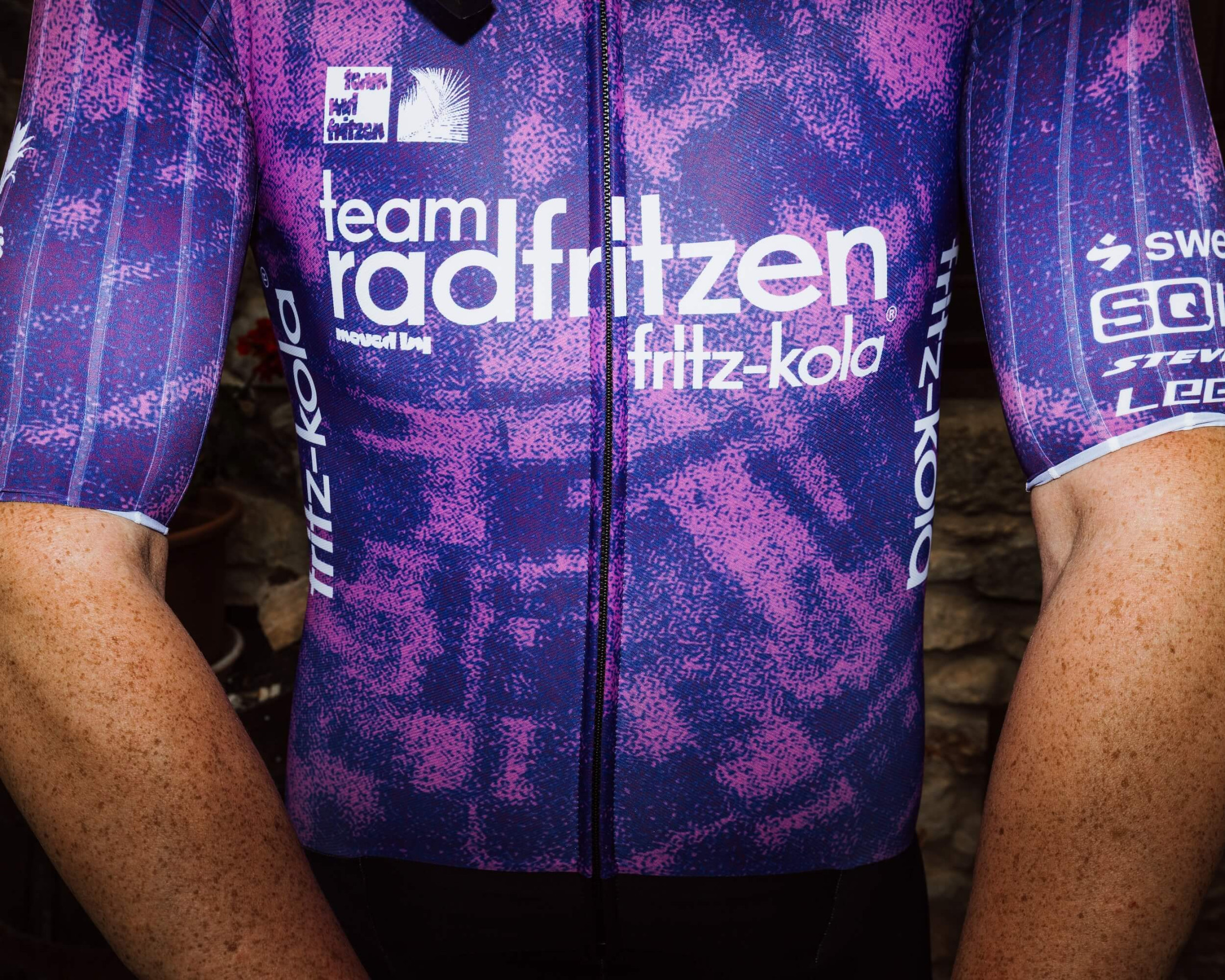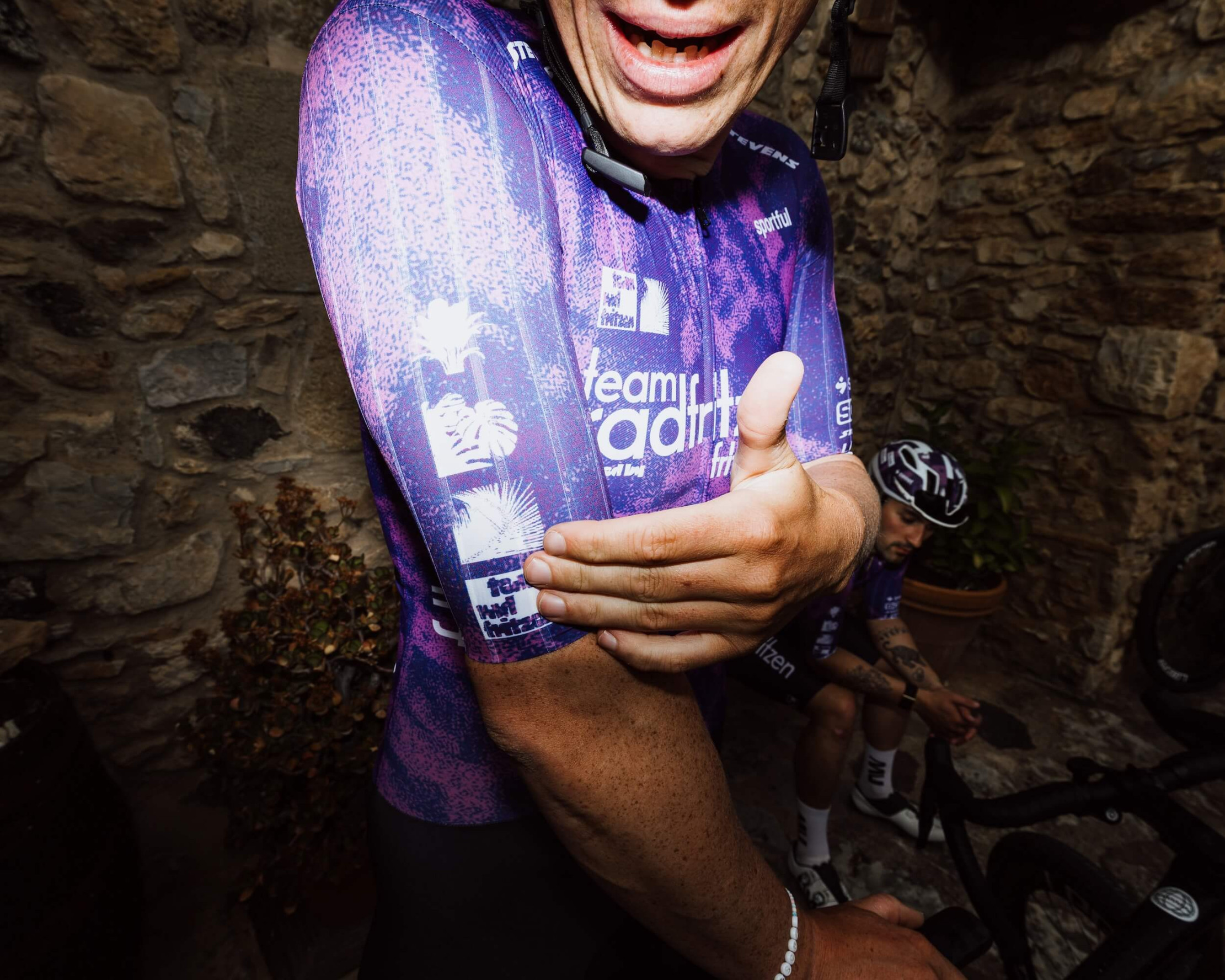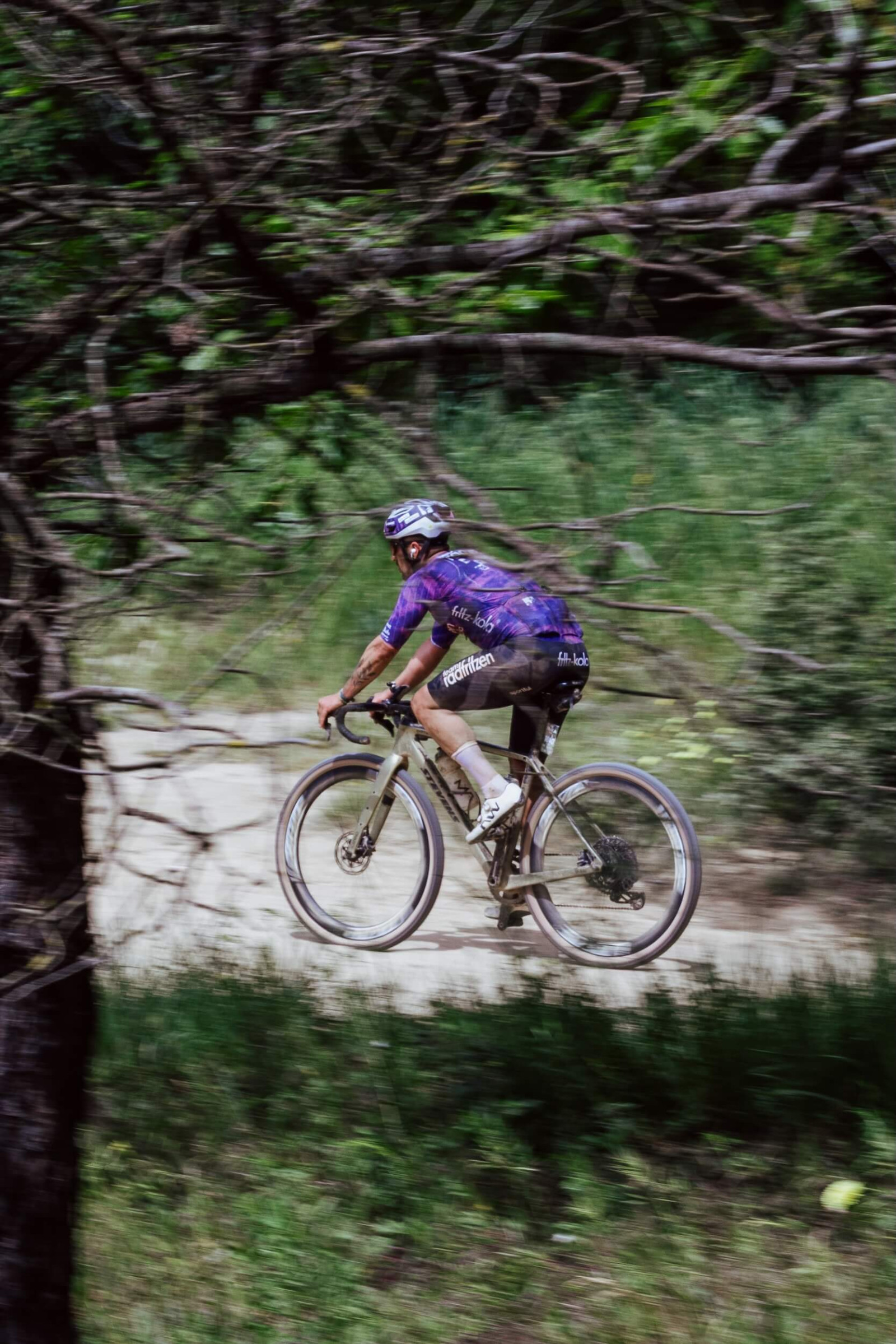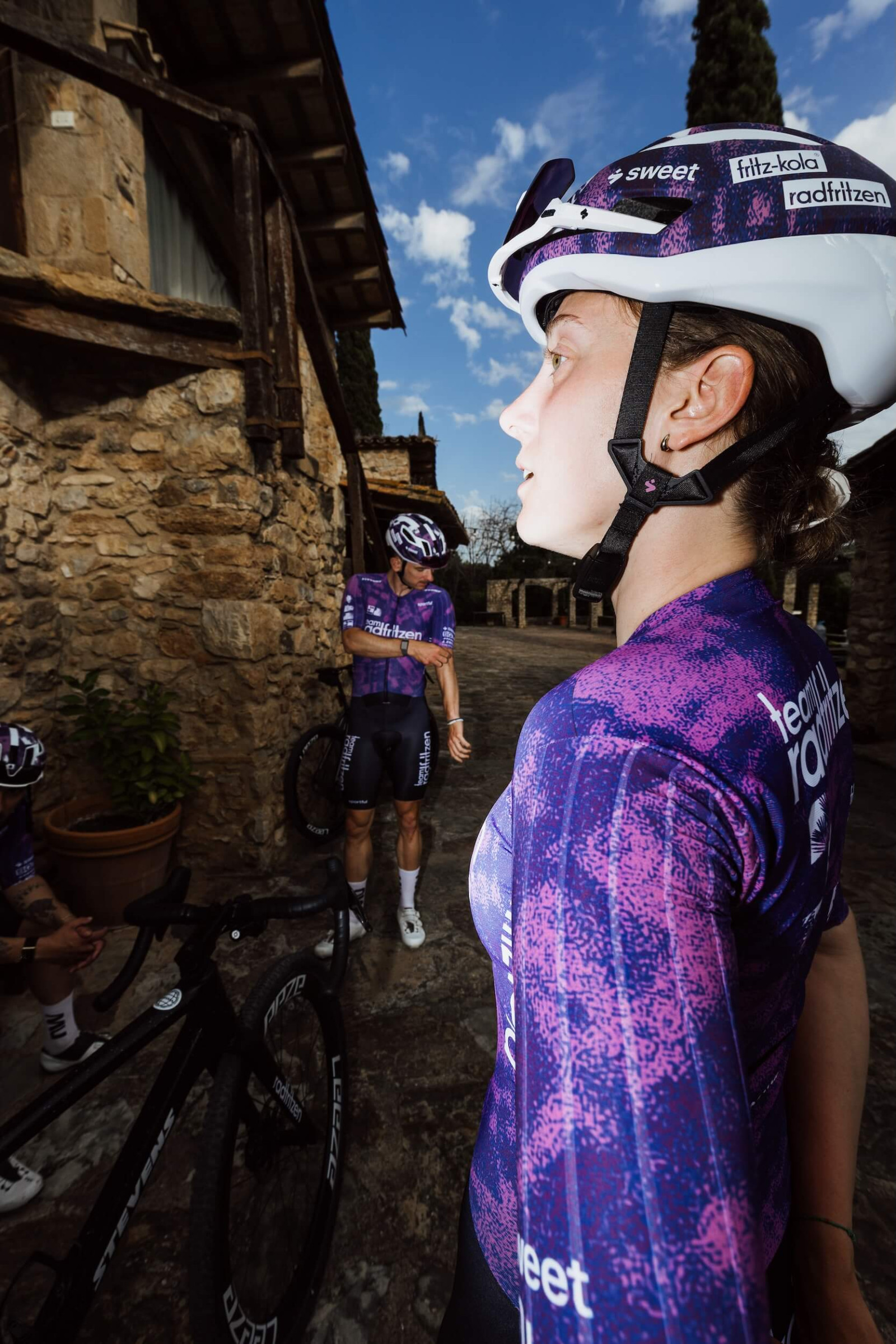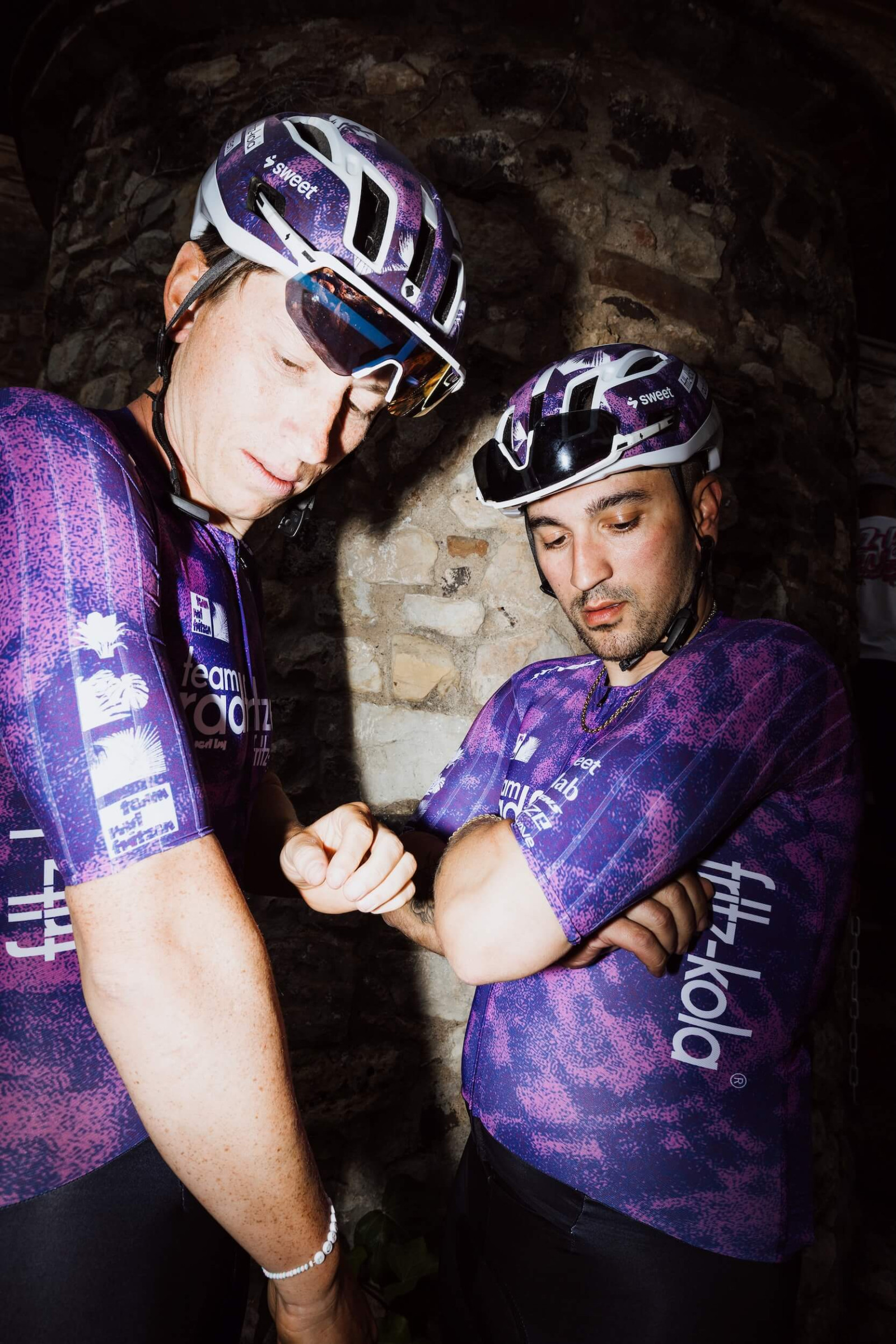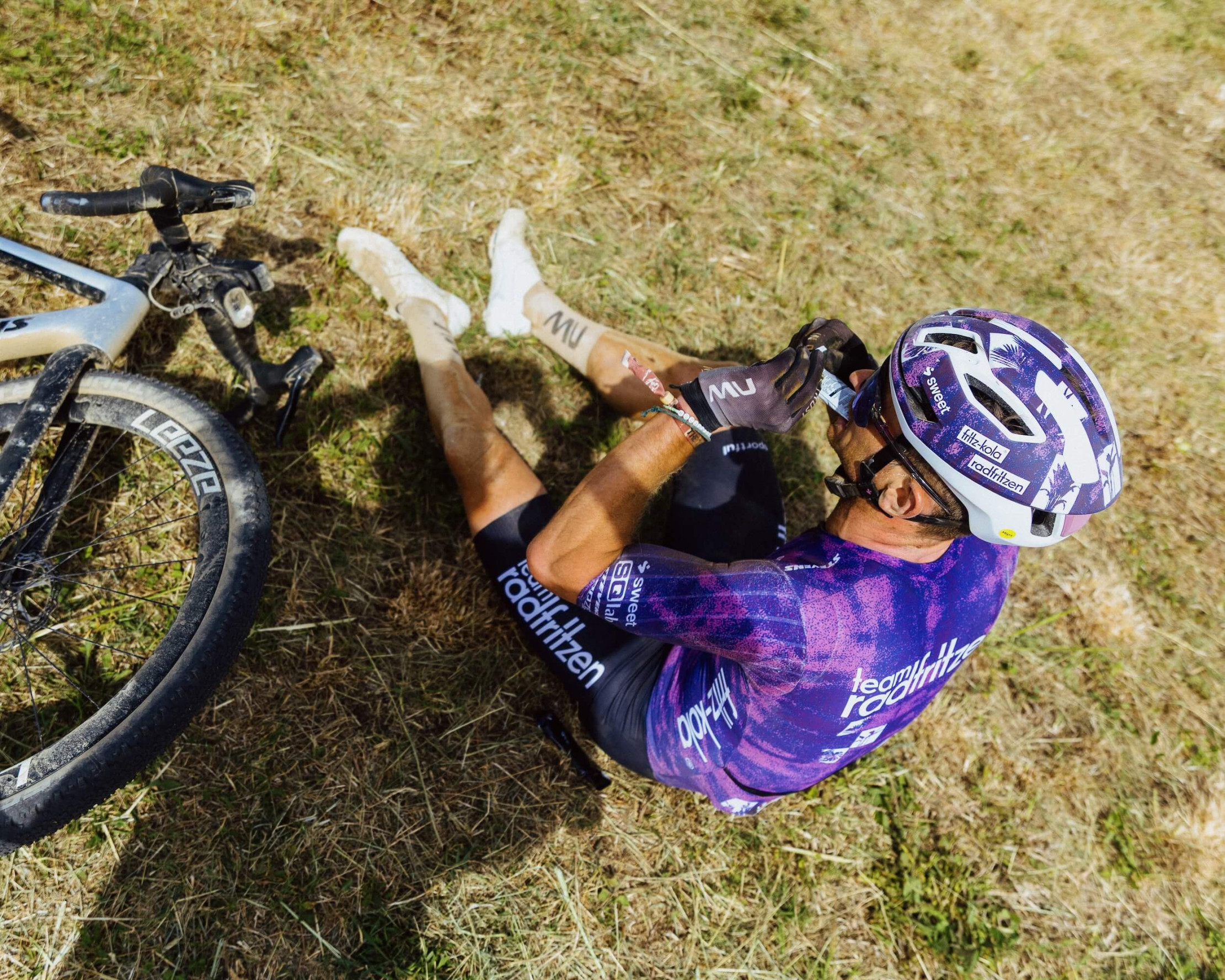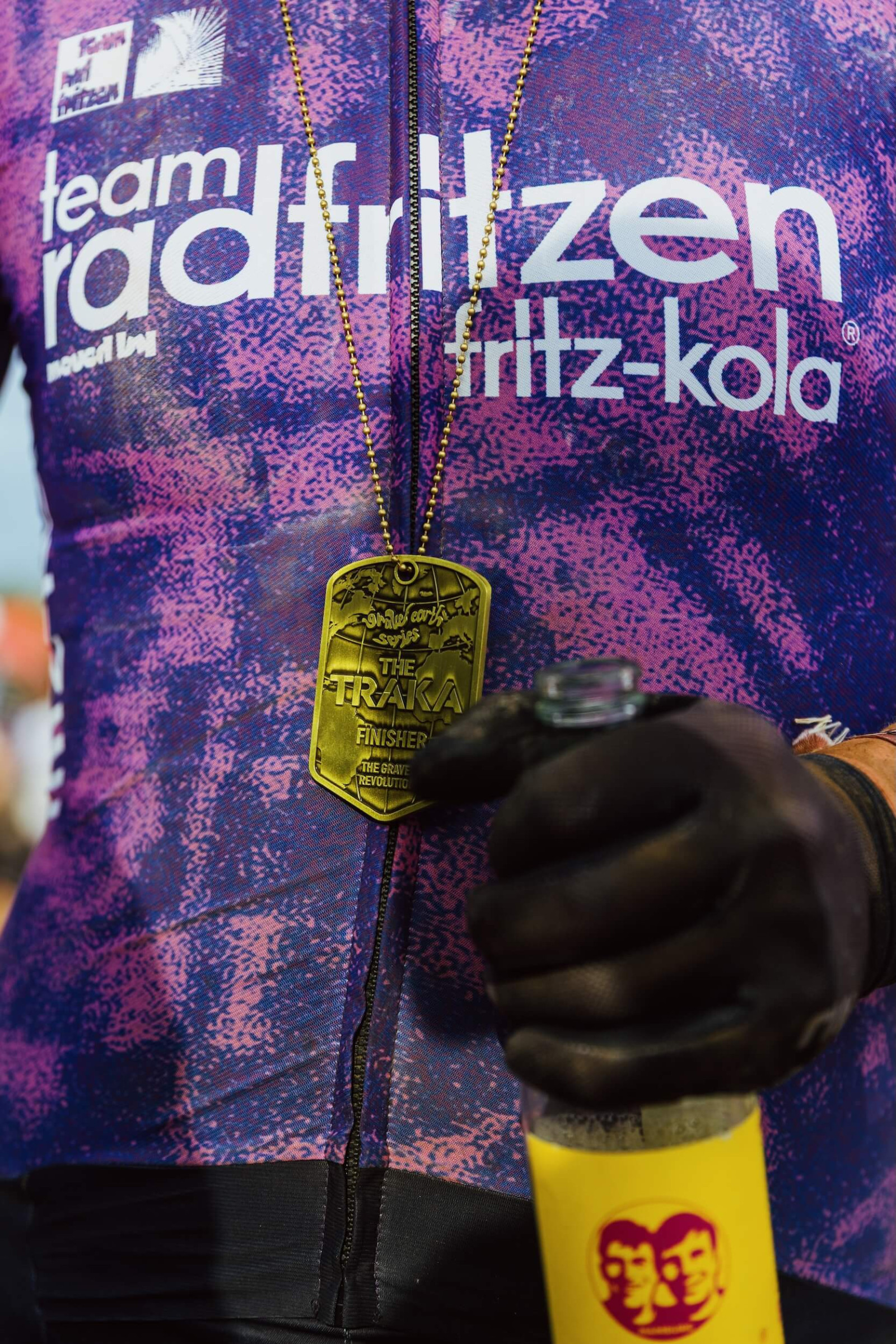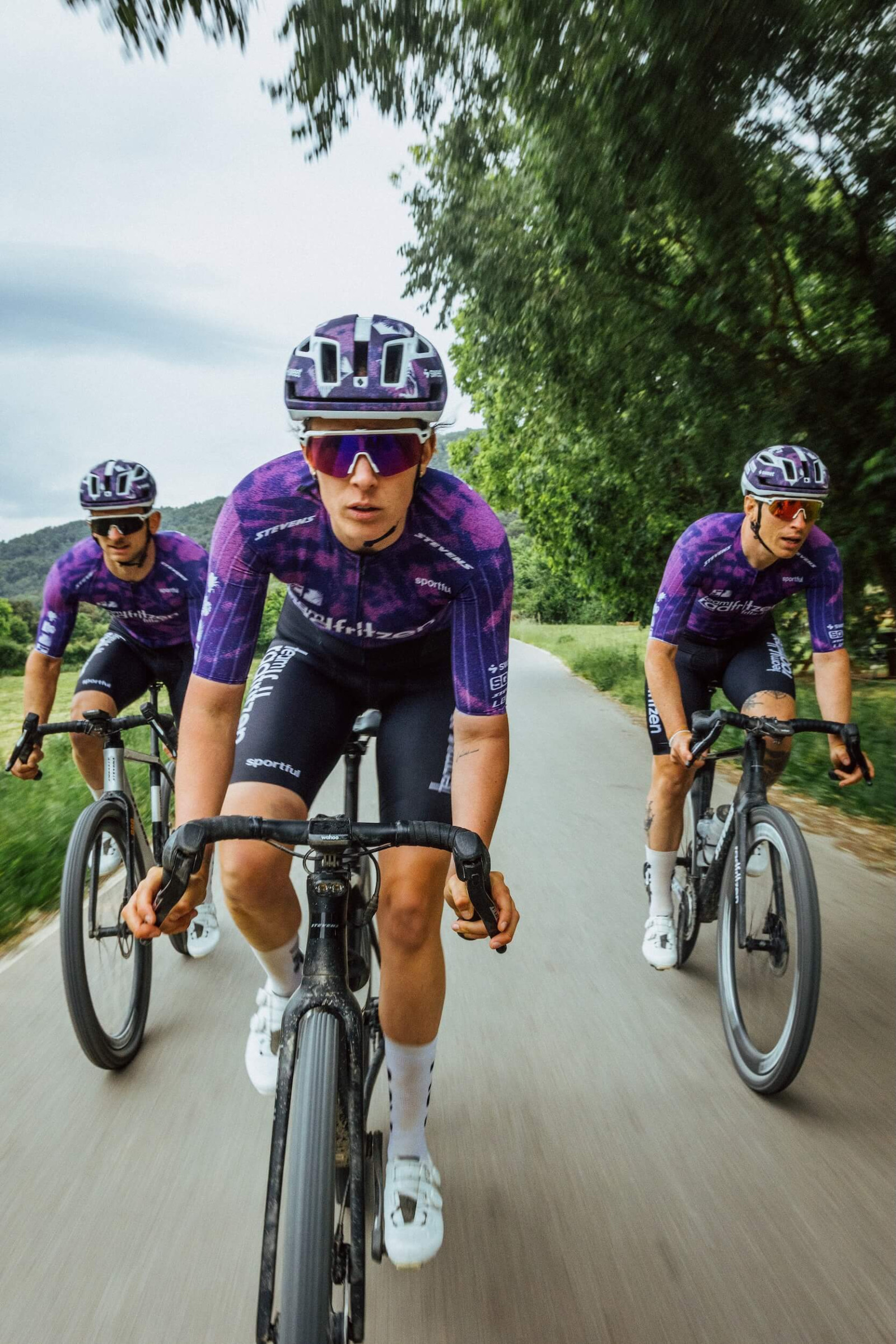
Team Radfritzen Team Kit 2026
Branding
In Zusammenarbeit mit Team Radfritzen aus Hamburg und dem Radbekleidungshersteller Sportful aus Italien ist das neue Team-Kit für die Saison 2026 entstanden. Die Gestaltung orientiert sich visuell am Charakter des Gravelradsports: rau, dynamisch und landschaftlich geprägt. Das violett-pinke Pattern erinnert an abstrahierte Terrain- und Landschaftsstrukturen und verleiht den Trikots und Renneinteilern eine markante, eigenständige Identität.
Das Pattern wird durch weiße Sticker-Elemente, in denen abstrahierte Pflanzenformen erkennbar sind ergänzt. Gemeinsam mit den großflächig eingesetzten Sponsorenlogos entsteht ein spannungsreicher Kontrast zwischen organischen Formen und klarer Typografie. Die konsequente grafische Umsetzung sorgt in Kombination mit dem Pattern für einen starken Wiedererkennungswert.
Zusätzlich dazu ist gemeinsam mit Sweet Protection ein individuell gestalteter Helm für das Team entstande. Das Pattern des Kits wurde vollflächig auf den Helm übertragen und durch die weißen Sticker-Elemente gezielt aufgebrochen. Sponsorenlogos und farbige Details fügen sich in die Gesamterscheinung ein.